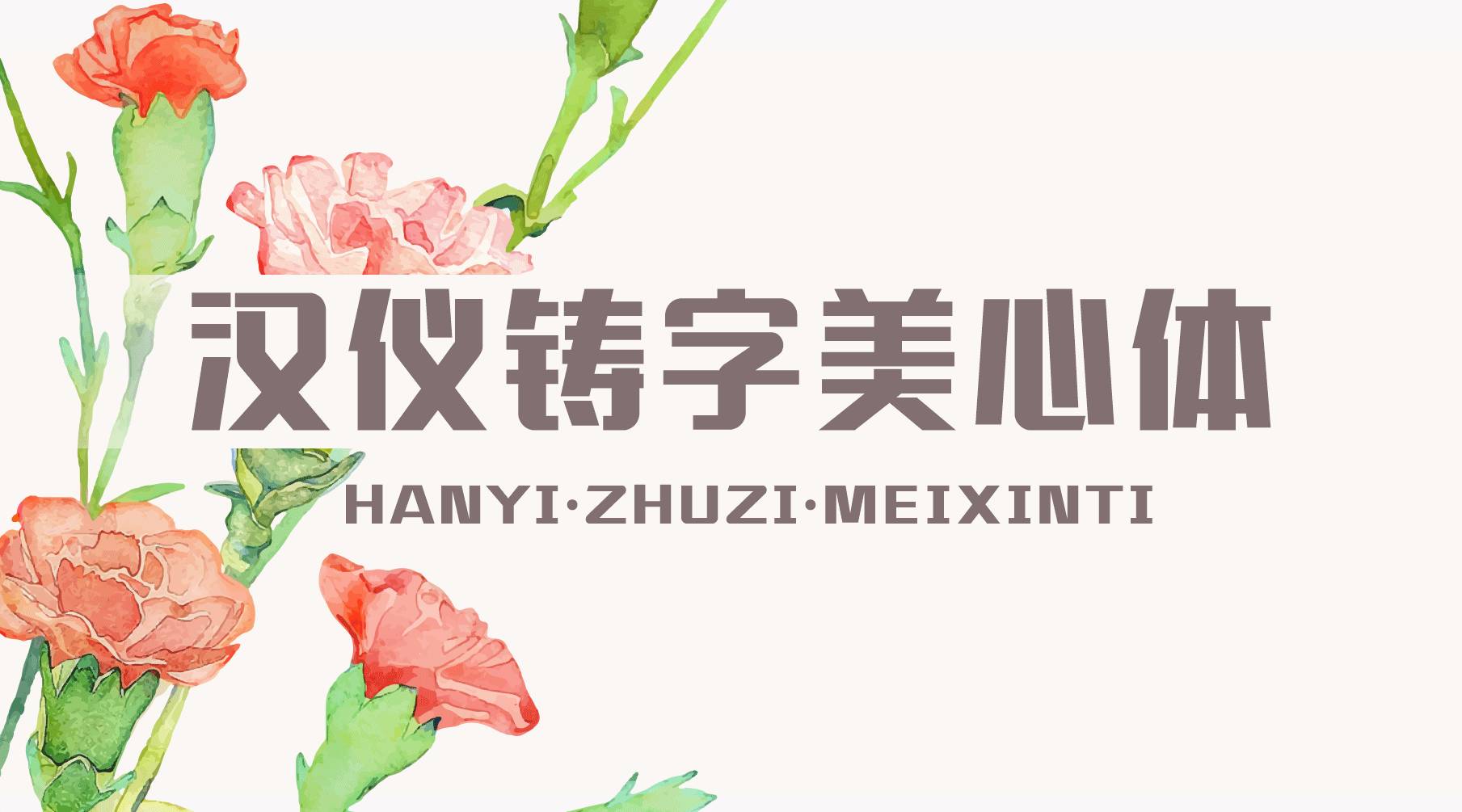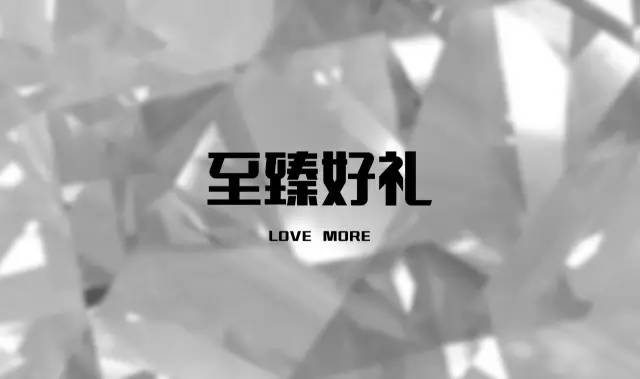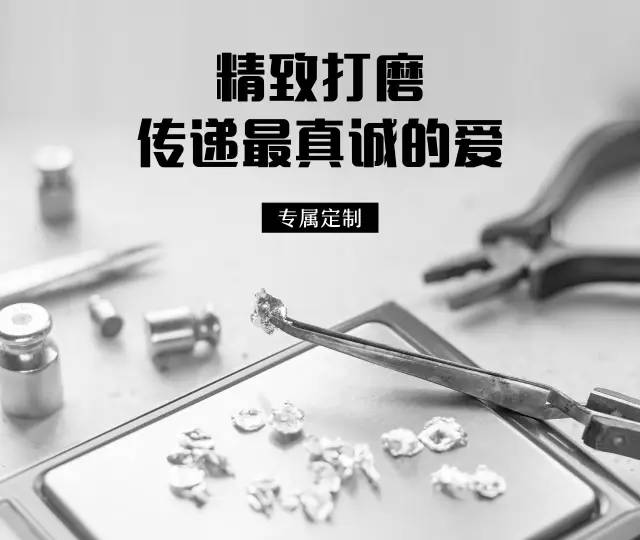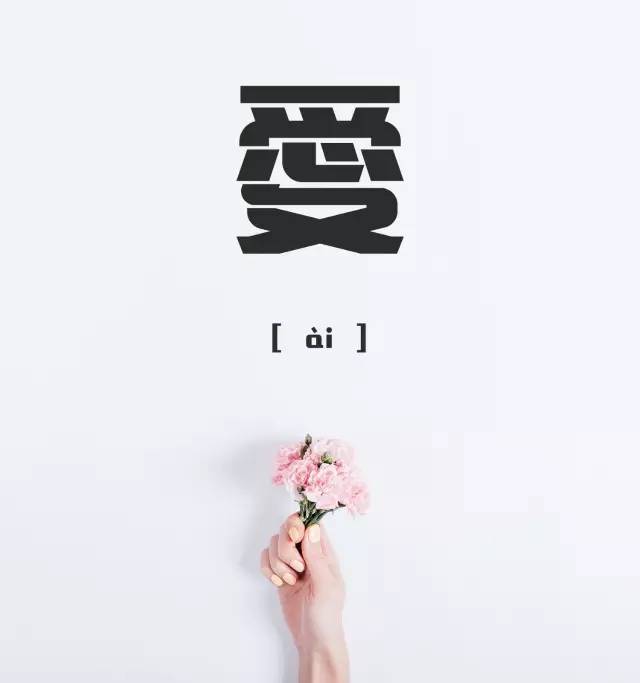
汉仪铸字美心体介绍,汉仪铸字美心体特点、适用场景
/ 汉仪铸字美心体 /
专属节日 × 女性标题字体
标题字,区别于正文字,是一种适合用作标题的字体。标题字的风格特点突出、醒目,笔画设计多根据其字体内部结构关系,展开更多个性化变化,较适用于少量字数的标题排版设计。
那么,
哪些标题字更具备女性特质的呢?
新品汉仪铸字美心体 + 6款精选字体,
新品字体
汉仪铸字美心体 ︳一款刚中带柔的标题字体
现代 / 时尚 / 女性 / 优雅 / 运动 / 有力 / 稳重
标志 / 广告 / 游戏 / 动漫 / 影视 / 包装
节日属性
情人节 / 妇女节 / 母亲节 / 七夕节等
字体特征解读
精简笔画,连接处理
在保证字体识别度的前提下,部分字体在“撇”的设计上进行了简化处理,右上角与横的部分则做了连接处理。
外圆内方,刚柔并济
字体笔画横平竖直,横竖为一比二的比例设定,所有口的特点统一采用外圆内方的设计,也照应了天圆地方的布局,让字体看起来方中带圆,刚柔并济。
字面伸展,刚柔并济
字体的笔画设计在可控的范围内以最大限度的“伸展”,中宫外扩的处理让字体看起来更加端正挺拔。
粗细均匀,视觉统一
注重笔画的粗细处理,特别是在多笔画的情况下,笔画较粗的字体力求粗细均匀、主辅分明,而对于一些细节也做了特殊的加工。
字体应用模拟展示
这款字体刚中带柔,设计师们可以根据不同产品的需求将这款字体发挥出不同的特质,适用在更多种类的场景当中。